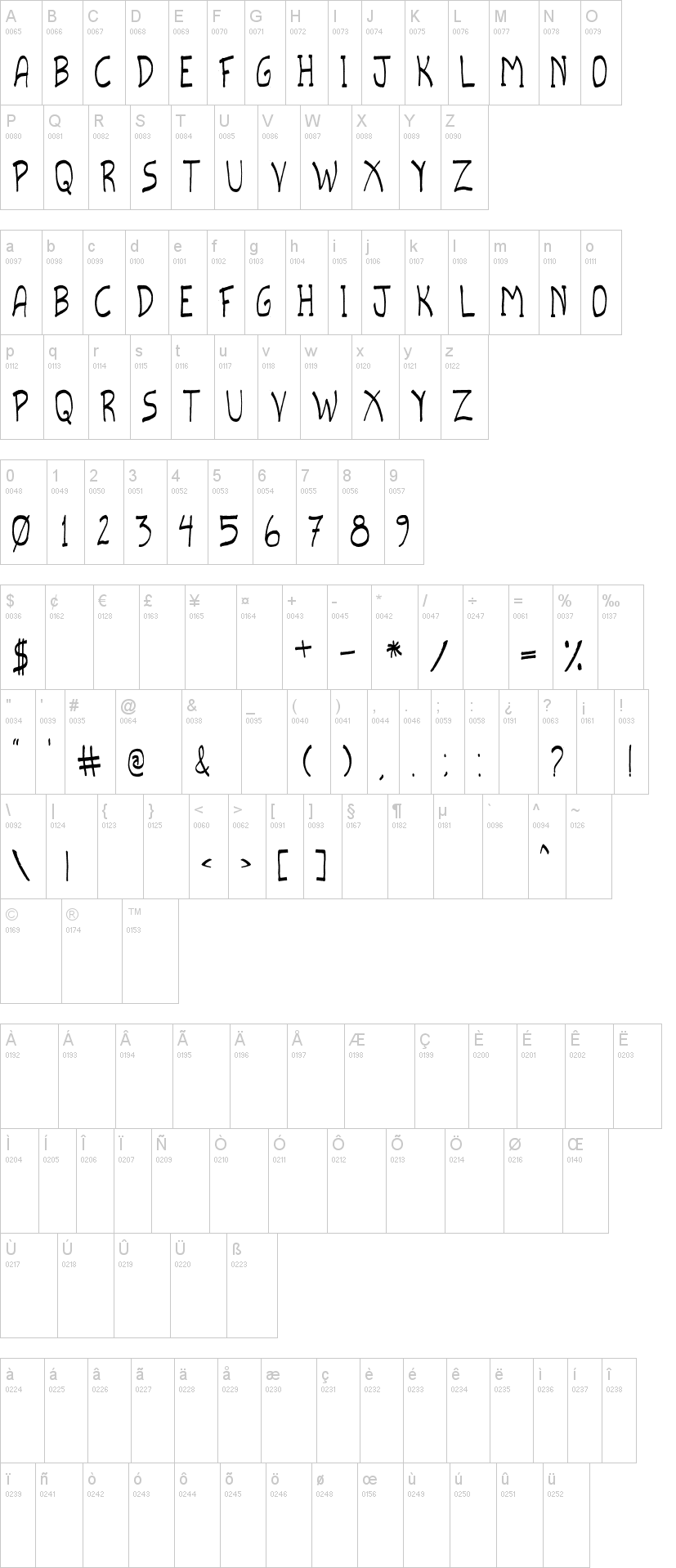
Scripto TFB是一种脚本风格的字体,其名称中的TFB代表 "TypeFaceBuilder",意为"字体构建器"。Scripto TFB的字母和符号都具有弯曲的线条和手写的风格,类似于人类手写的草书。这种字体可以用于设计各种类型的项目,如卡片、海报、标志和网站设计等。Scripto TFB 字体的设计者是TypeFaceBuilder字体设计工作室,并于2001年首次推出。Scripto TFB 字体可用于个人和商业项目,但需要购买授权才能在商业项目中使用。内容介绍
Scripto TFB是一款非常不错的手写艺术字体,具有很好的视觉感,适合于文化类的宣传设计、商业类品牌的广告和产品包装设计以及个性化文字排版等较多场景。